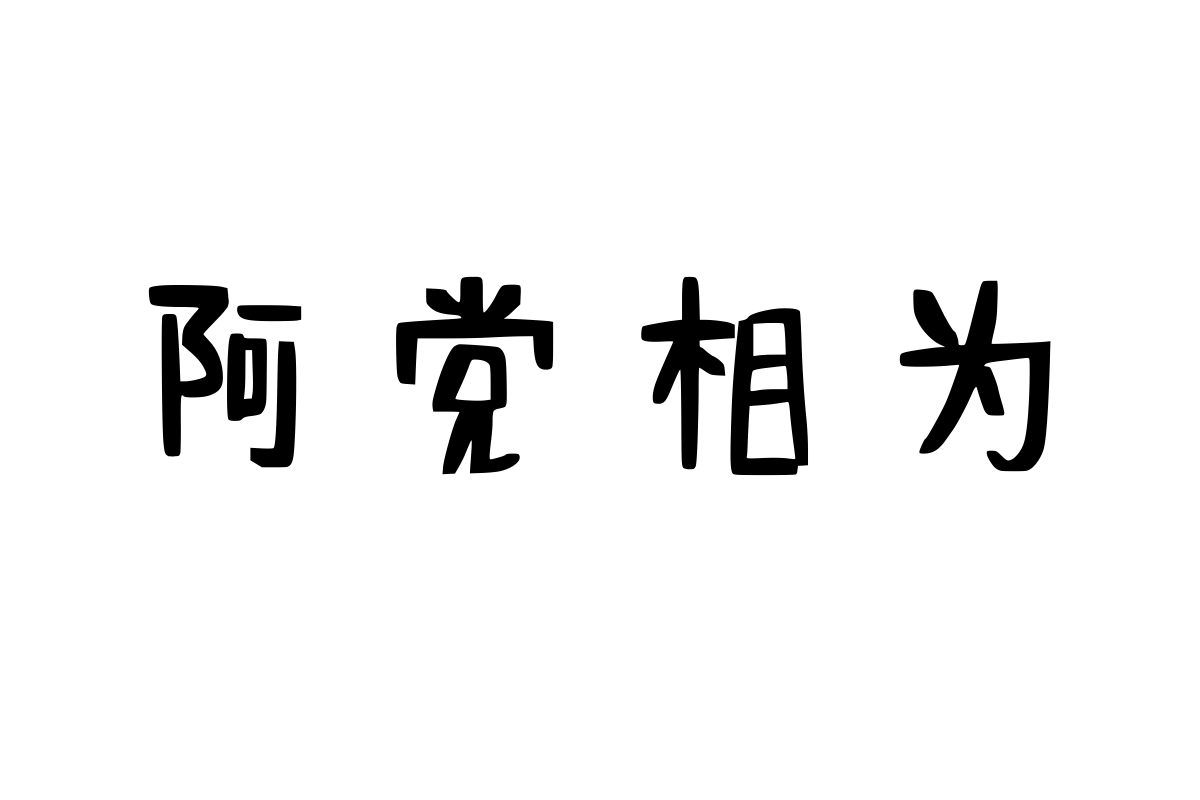
兰米自然萌加粗是一款中文字体,它的特点是具有可爱的风格,给人一种温馨、亲切的感觉。这款字体的特点在于它的笔画粗细适中,线条流畅自然,适合用于儿童书籍、儿童杂志、儿童网站等需要表现可爱风格的场合。同时,兰米自然萌加粗也适用于需要强调重点的文本,可以通过改变字体大小和粗细来突出重点内容。总的来说,兰米自然萌加粗是一款适合各种场景使用的可爱风格中文字体。